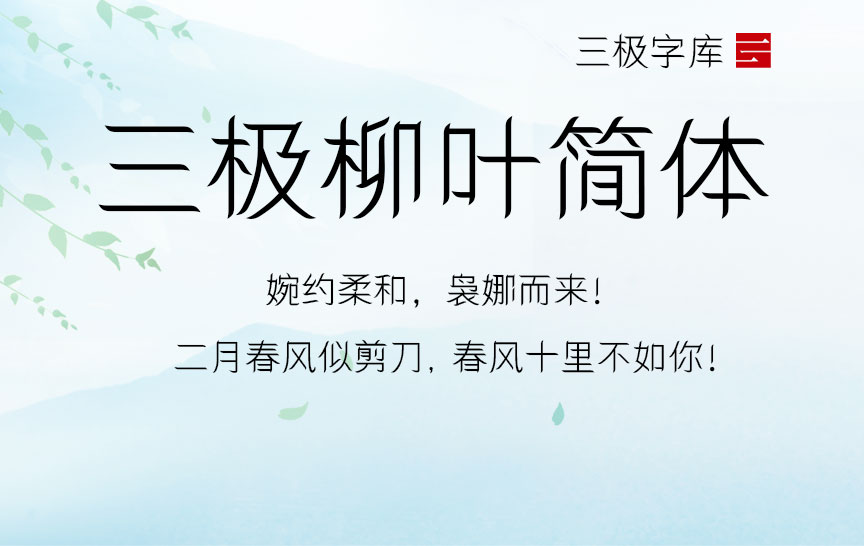
三极柳叶简体,作品整体风格轻巧简洁,笔画飘逸、平直,粗细匀称,起笔收笔为柳叶状,折、钩转折明显,细节刻画鲜明。它的灵感来源于柳叶,弱柳扶风,江水初平。给人一种温暖亲切,干净利落的感觉,具有婉约柔和的气质。视觉效果字体方正稳健又有柳叶的飘荡动感,节奏感明显,实用性强。本作品适用于印刷媒介的标题与正文排版、各类屏幕显示及影视字幕等。